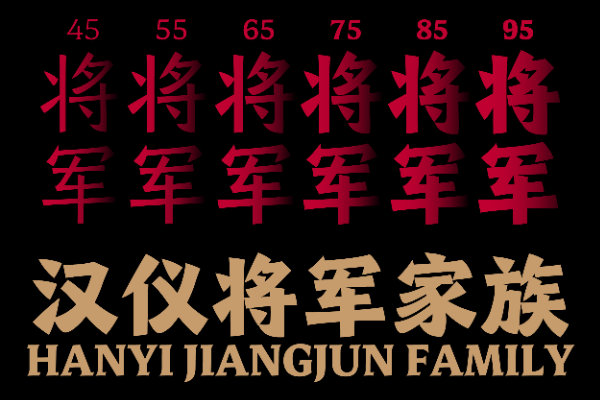
汉仪将军 55W
一款有着碑刻感、充满了力量的标题字。这款字体结构方正、中宫宽绰、字形挺拔,字如其名般有着力拔山河气盖世的将军气质。汉仪将军的日文与西文也有其独特的地方,日文假名的书写感较中文更强,西文也因为书写工具不同,在常规衬线体的基础上加入了刀刻感,更加方正有力量。汉仪将军的中日西文既有共同的基因,也有不同的细节差异。汉仪将军的标题属性在组版时因为这种共性和异性反而会增加跳跃感。